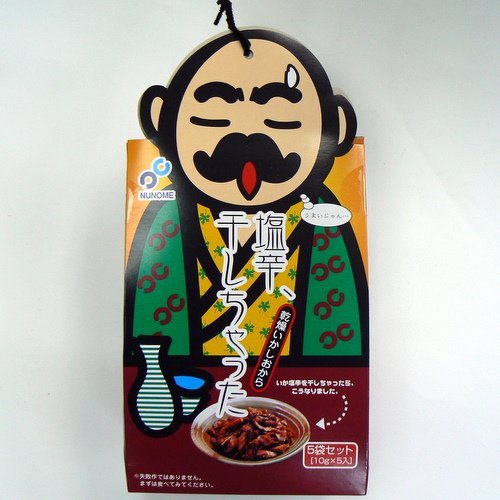
塩辛、干しちゃった
株式会社布目の「塩辛、干しちゃった」シリーズにダイナフォント 金文体が採用されている。
商品名をストレートに表現したネーミングタイトルと、キャラクターなどを取り入れた遊び心を取り入れたパッケージデザインで「第15回 北の生活産業デザインコンペティション銀賞」受賞。
塩辛、干しちゃったシリーズのタイトルにダイナフォント金文体が採用
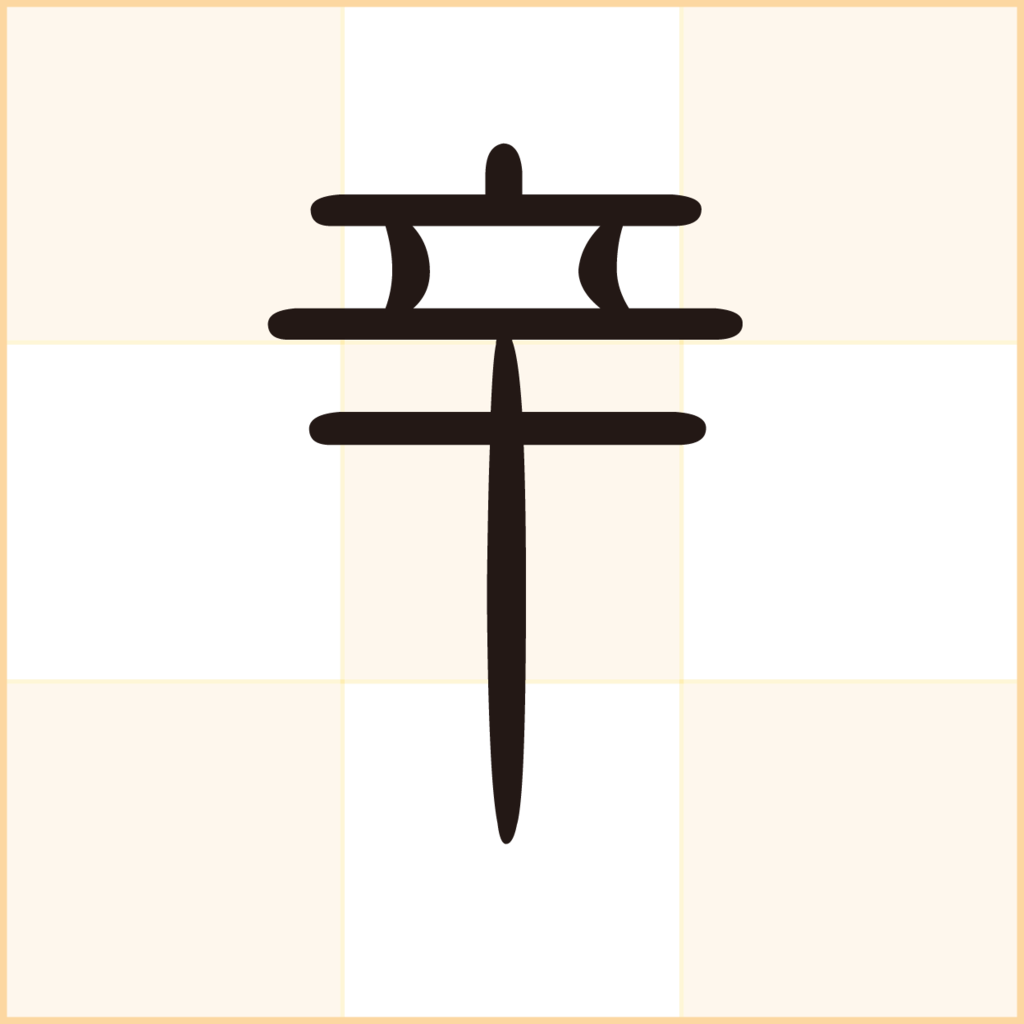
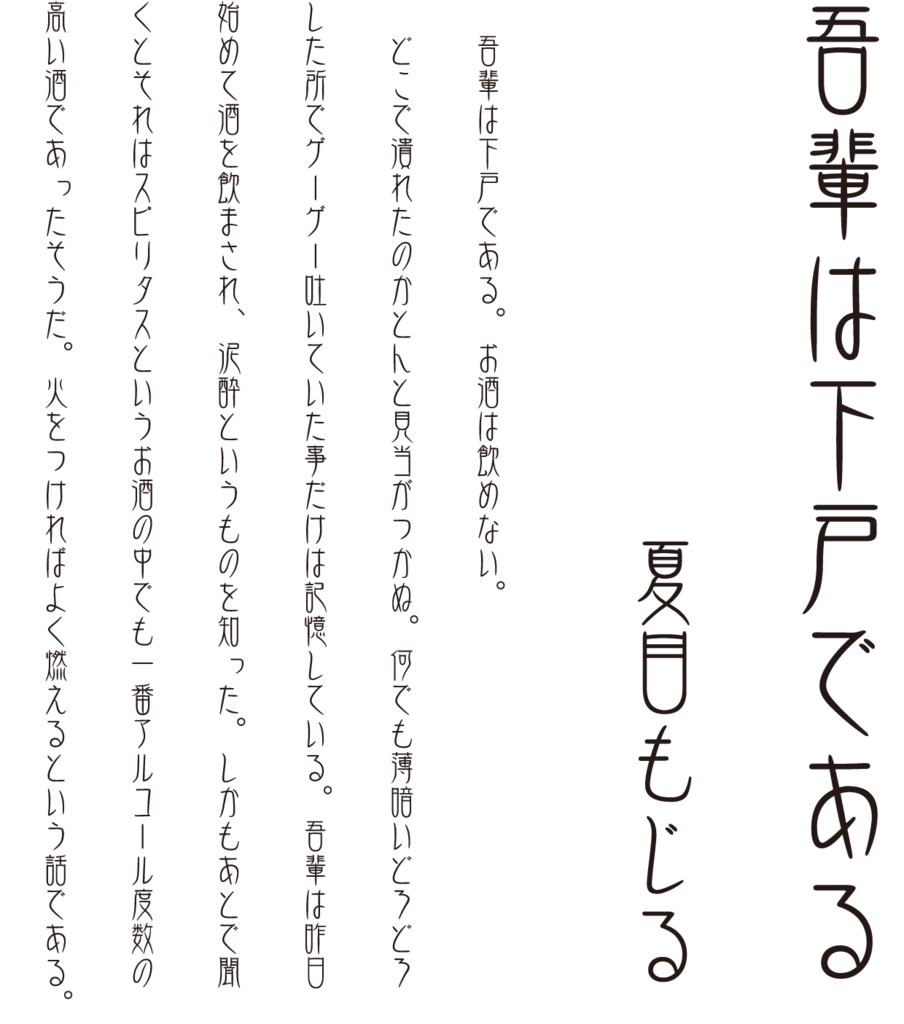
金文体
中国戦国時代の“中山王方壺”に鋳込み刻まれた金文を元にして、そのイメージを壊さずに神秘性や独創性を高め現代的な感覚でリデザインされたダイナフォントの代表的な書体。